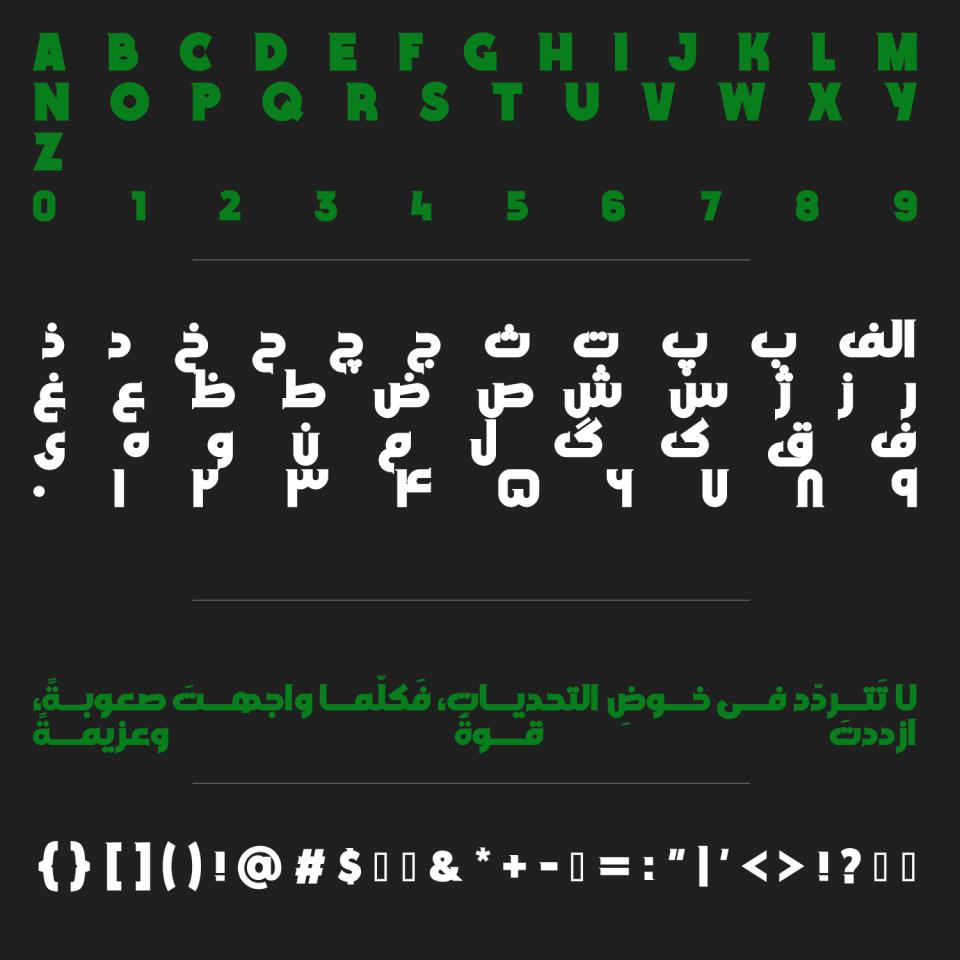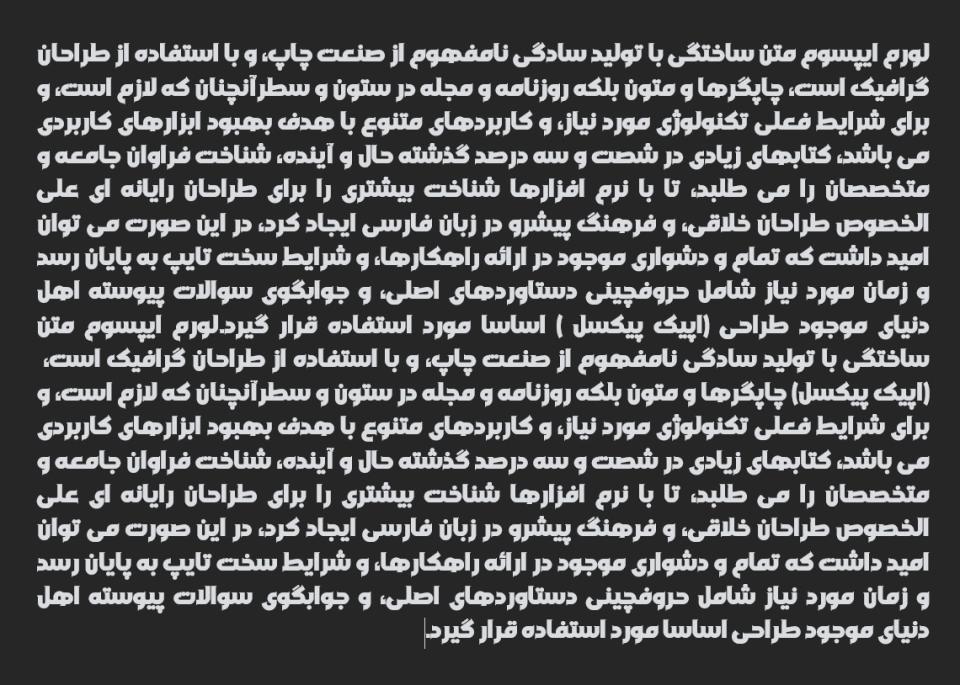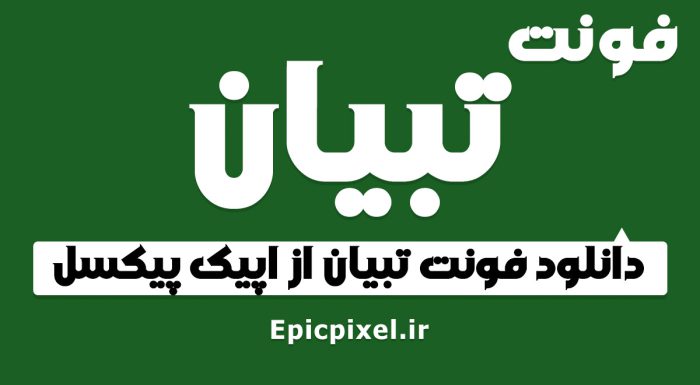
فونت تبیان، با طراحی منحصربه فرد خود، خوانایی متون فارسی را در محیط های دیجیتال بهبود می بخشد. این فونت با ساختار چشم نواز حروف، تجربه ای لذت بخش از مطالعه را برای کاربران فراهم می کند. تبیان، با رعایت اصول زیبایی شناختی در طراحی، ظاهری مدرن و حرفه ای به نوشته های شما می بخشد و به همین دلیل، برای استفاده در وب سایت ها، اسناد چاپی و طراحی های گرافیکی، انتخابی ایده آل است.
یکی از ویژگی های برجسته فونت تبیان، هماهنگی بالای آن با زبان فارسی است. این فونت با دقت فراوان، تمام ظرافت ها و ویژگی های خاص نوشتار فارسی را در خود جای داده و از این رو، متونی روان و خوانا را ارائه می دهد. استفاده از فونت تبیان، به نوشته های شما هویتی بصری می بخشد که به راحتی در ذهن مخاطب ماندگار می شود. این فونت، با ایجاد تعادل بین فرم و محتوا، به انتقال بهتر پیام شما کمک می کند.
اگر به دنبال فونتی هستید که هم زیبایی بصری داشته باشد و هم خوانایی بالایی را ارائه دهد، فونت تبیان گزینه ای بی نظیر است. این فونت، با طراحی دقیق و حرفه ای خود، سطح جدیدی از کیفیت را در نوشته های فارسی به نمایش می گذارد.